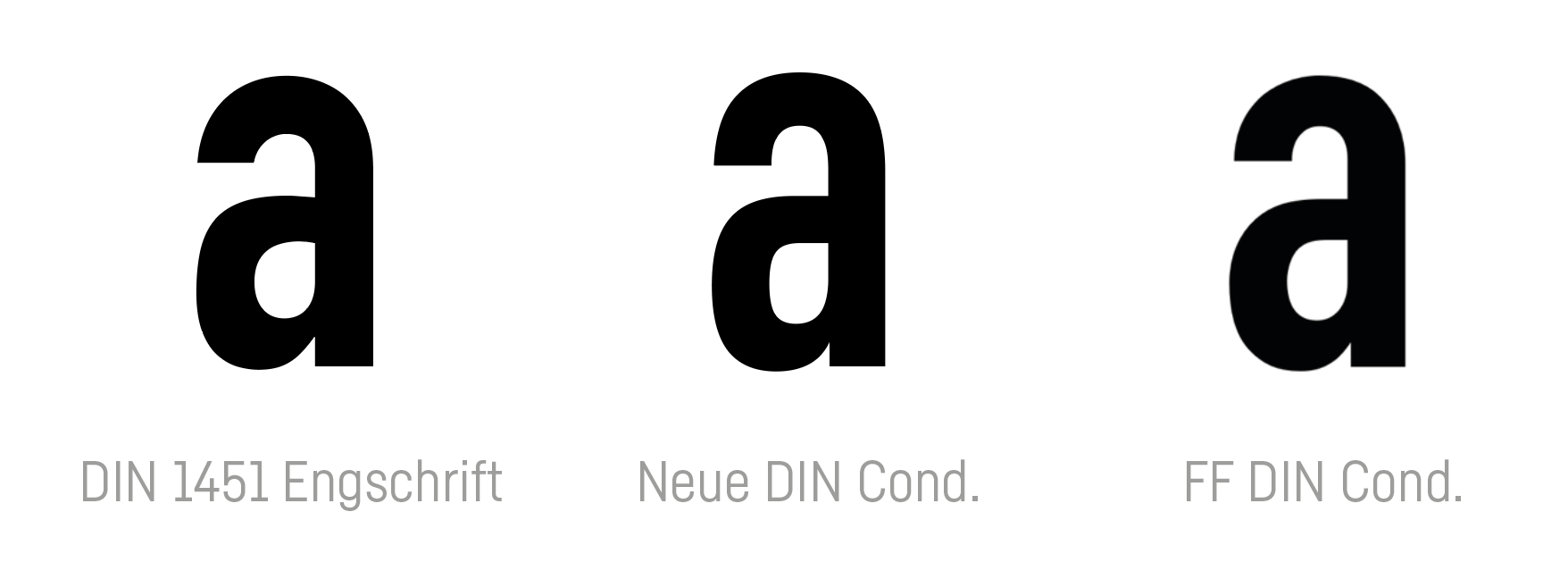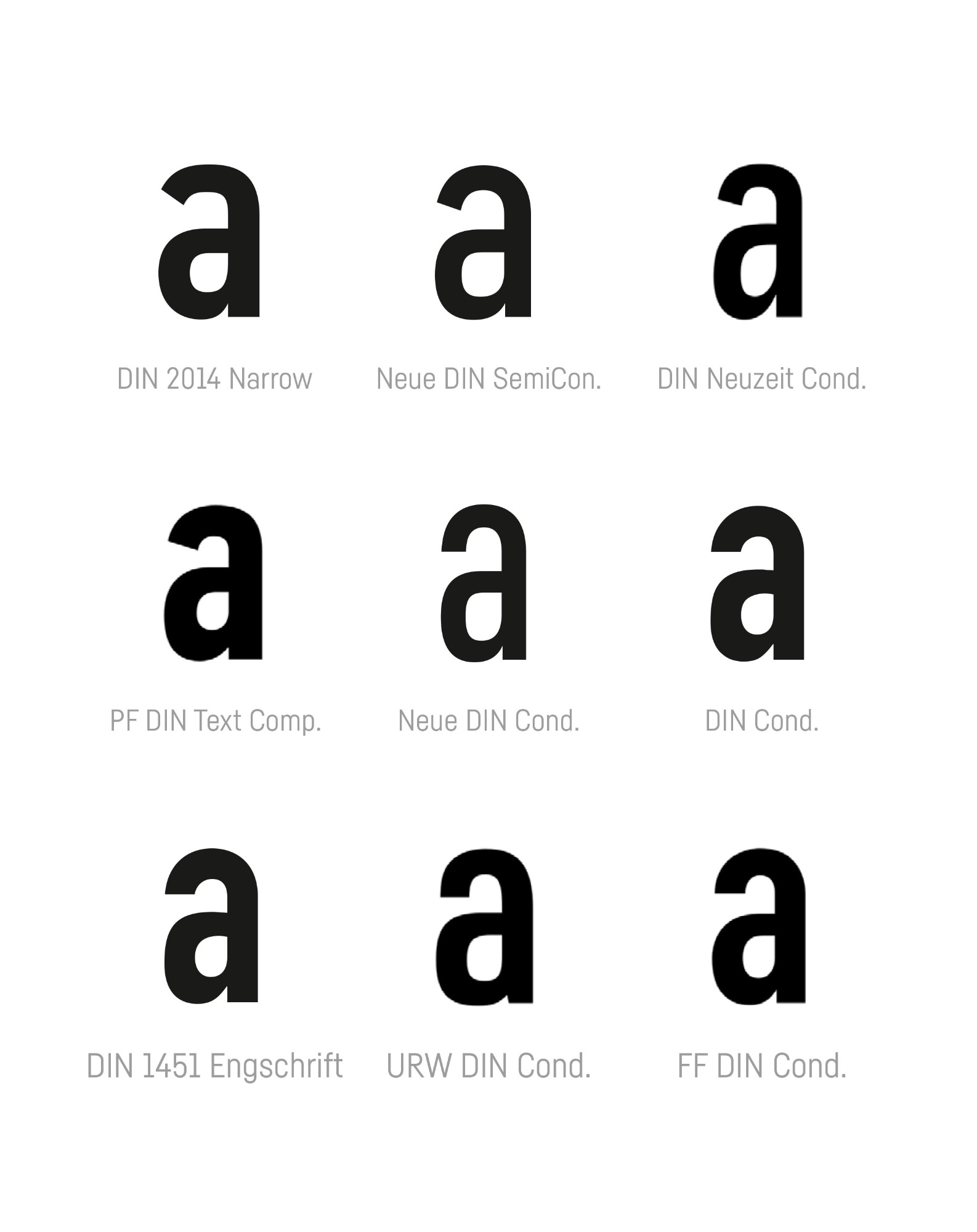
An welchen Glyphen bzw. an welchen Formen machst du das fest?
sieht für mich allgemein mehr nach DIN aus weil die formen nicht so geschlossen sind.
dann einfach nicht DIN nennen und fertig.
Damit ist es aber keine DIN mehr, sondern eine Interpretation.
Aber wo soll man denn da die Grenzen ziehen? Wann darf man bei einer Weiterentwicklung noch den Namen weiterführen, wann nicht?
Wenn wir in die Geschichte zurück schauen, gab es ja schon ähnliche Fälle, wie zum Beispiel bei der Helvetica. Bei der Neuen Helvetica kamen auch extreme Weiten und Strichstärken hinzu, welche es vorher nicht gab. Diese isoliert betrachtet, dürfte man auf den ersten Blick auch nicht unbedingt gleich als Helvetica erkannt haben. Bei der Helvetica Now hat man zusätzlich Alternativ-Buchstaben, optische Größen usw. hinzugefügt. Wenn man dann diesen letzten Entwicklungsstand mit der ursprünglichen Helvetica vergleicht, liegen da inzwischen auch Welten dazwischen.
sieht für mich allgemein mehr nach DIN aus weil die formen nicht so geschlossen sind.
Es gibt im DIN-Universum sowohl offen als auch geschlossen. Ich kann deinen Eindruck leider immer noch nicht nachvollziehen ... vielleicht schaust du dir die verschiedenen DINs noch mal näher an. Die Unterschiede sind mitunter beachtlich und das betrifft nicht nur die Neue DIN.
die neue DIN wechselt ja selbst von offen zu geschlossen, je schmaler umso geschlossener.
Genauso wie bei der DIN 1451 (siehe Fette Engschrift, Mittelschrift, Breitschrift). :-? Hatten wir auch schon. ;-)
aber nicht innerhalb einer familie. bzw. es geht mir ja um die XXschnitte, die neue DIN wechselt ja selbst von offen zu geschlossen, je schmaler umso geschlossener.
Ach Robert ... mach dir doch mal die Mühe und schau dir die FF DIN richtig an. Das a beispielsweise schließt sich bei der FF DIN Condensed genauso wie bei den schmalen Schnitten der Neuen DIN.
innerhalb einer superfamilie find ich das etwas komisch.
Das kannst du auch gerne finden. Aber bitte nicht behaupten es wäre bei der Neuen DIN anders als bei der FF DIN oder den Ursprüngen der DIN und darum geht es ja hier ...
mir geht darum das die DIN in den schmalen schnitten für mich nicht mehr zu erkennen ist, sieht man diese gelöst von dem rest der familie.
Was ist da nicht mehr zu erkennen? Ich sehe es leider nicht ...
wo habe ich das denn behauptet?
Du hast als erste Reaktion auf den Link zur Neuen DIN geschrieben:
wobei das mit DIN nix mehr zu tun hat, der name ist wohl eher marketing.
Mittlerweile bist du nur noch bei den schmalen Schnitten die wiederum aber sehr nah an den schmalen Schnitten der FF DIN oder DIN Engschrift sind (Siehe Abbildung weiter oben). Deshalb hier noch einmal die Frage aufgrund welcher Unterschiede die Neue DIN für dich keine DIN ist.
Du hast als erste Reaktion auf den Link ...
genau, das ist mein subjektiver eindruck was die XXformen betrifft davon spreche ich die ganze zeit. mit schmalen meinte ich XX, war evtl. missverständlich ausgedrückt.
Deshalb hier noch einmal die Frage aufgrund welcher Unterschiede die Neue DIN für dich keine DIN ist
welche DIN meinst du? 😜
in den XXschnitten sehe ich keine DIN. irgendwie drehen wir uns im kreis und ich glaube ich habe dazu alles gesagt. ist wie gesagt mein subjektiver eindruck, du darfst das gerne anders sehen.
in den XXschnitten sehe ich keine DIN.
Wie auch, die gab es in den extremen Schnitten ja auch nie. 😉
Dass sich die Buchstabenformen und insbesondere die -Abschlüsse entsprechend der verschiedenen Weiten anpassen (müssen), ist aus meiner Sicht absolut nachvollziehbar.
in den XXschnitten sehe ich keine DIN
Das ist ja schon mal eine ganz andere Aussage als zu Beginn wo die ganze Schriftfamilie »nix mit DIN zu tun hatte«. Die XX-Schnitte machen ja nur einen Bruchteil aus. Davon abgesehen unterscheiden sie sich im Aufbau kein Stück von der FF DIN Condensed oder der DIN 1451 Engschrift. Warum das eine für dich eine DIN ist und das andere nicht ist für mich nicht nachvollziehbar. Klar kann man das als persönliche Meinung deklarieren aber Argumente wären mir lieber gewesen. :roll:
Aber egal! Wie du schon sagst wir drehen uns im Kreis und sollten das Thema abschließen.
:trost:
Jetzt komme ich nicht mehr mit. Was ist verkehrt daran, dass man sich auf dich bezieht? Nach dem du deine Erkenntnisse publiziert hast ist es ja quasi unmöglich, dass jemand deinen Weg noch einmal geht und somit in die Geschichte der »DIN« eintaucht wie du es getan hast. Du hast dein Wissen geteilt und sie haben darauf aufgebaut. Das klingt für mich nach einem normalen und auch sinnvollen Prozess solange die Quellen genannt werden.
Das kann schon sein — aber auf Herangehensweisen gibt es eben keine Patente
Mir geht es nicht um irgendwelche Patente. Hab ich auch nicht behauptet.
Ich finde Eure Auslassungen total spannend!
Was haltet Ihr von der Parachute-Din? Die ist für mich die interessanteste, weil sie auch in einigen Geschmäckern auch polytonisches Griechisch kann 🙂
Mir geht es nicht um irgendwelche Patente. Hab ich auch nicht behauptet.
Habe ich behauptet es ginge dir um Patente? :-?